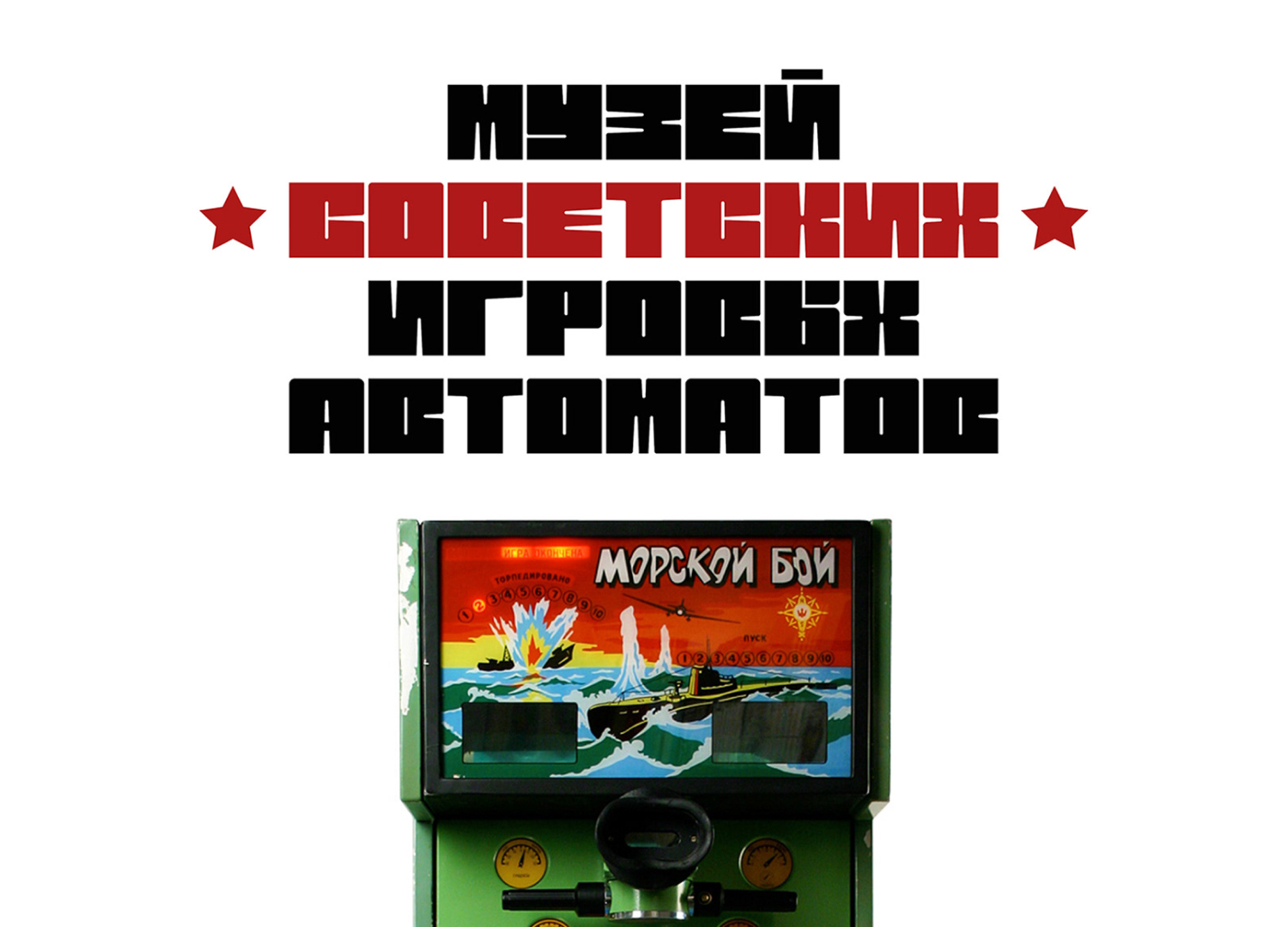
Бесплатный шрифт аркада
Аркада. Упитанный и необычный шрифт. В старой, игровой стилистике. Использовать стоит аккуратнее, чтобы совсем не расшатать его читаемость) Пухляши они такие.Бесплатно для всего) Автор: Oman Tverdunov